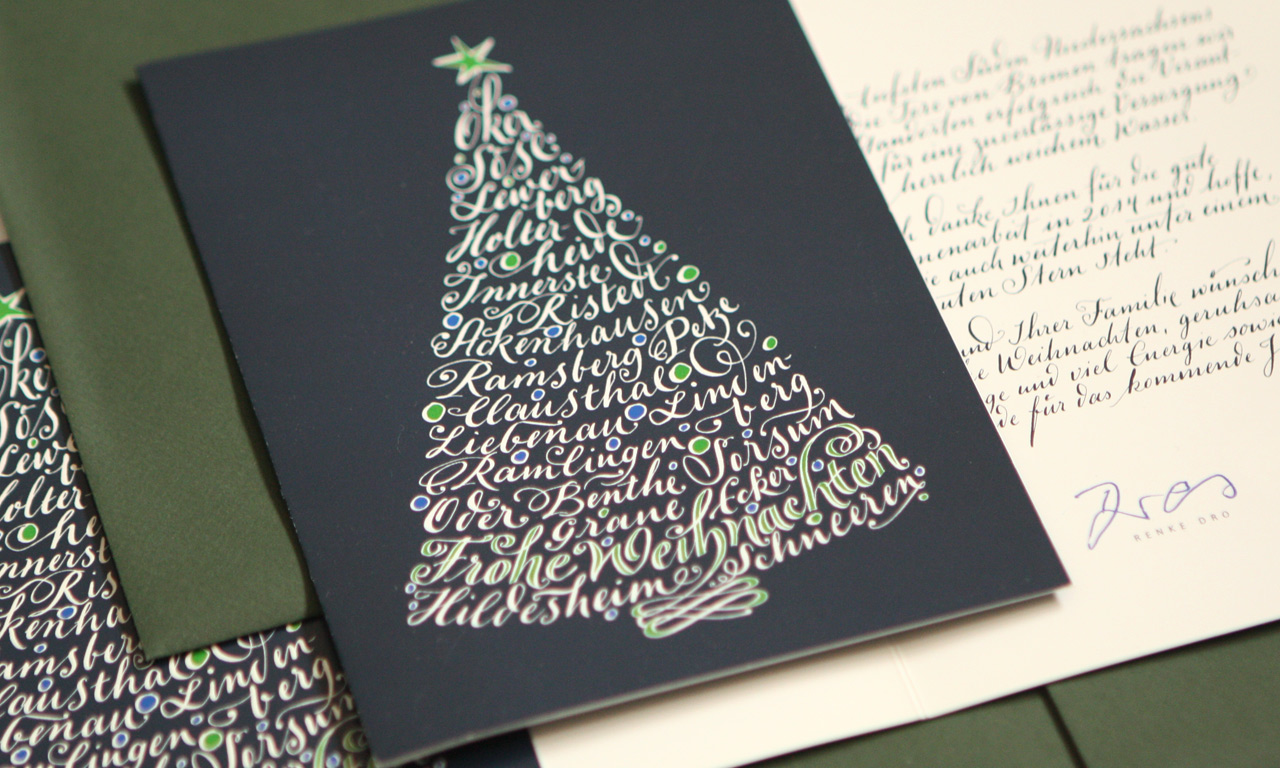
Kalligrafische Weihnachtskarte
Beratung, Entwurf in den Corporate-Design-Farben der Harzwasserwerke, Umsetzung des Textes (bestehend aus Namen von Talsperren und Flüssen) als illustrative Schriftcollage. Kalligrafische Umsetzung des Grußtextes im Innenteil im Schriftduktus des Hauptmotivs. Erstellung der Feindaten, Druckabwicklung.